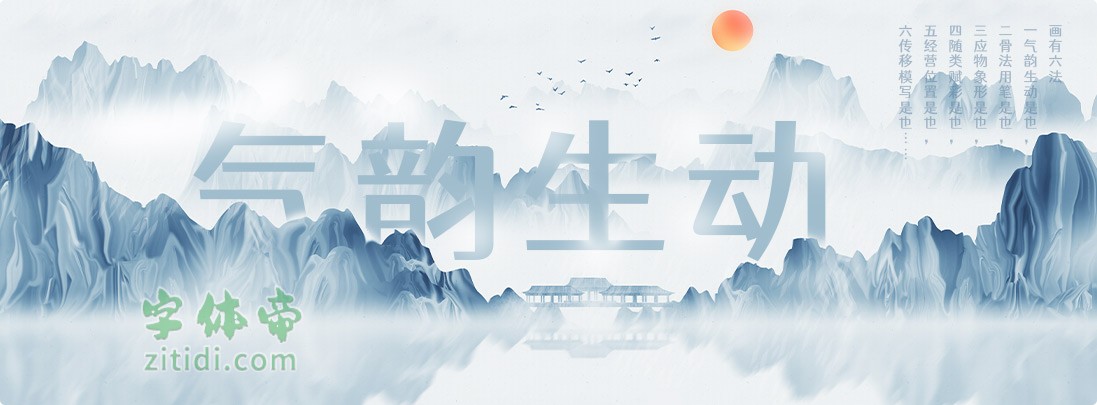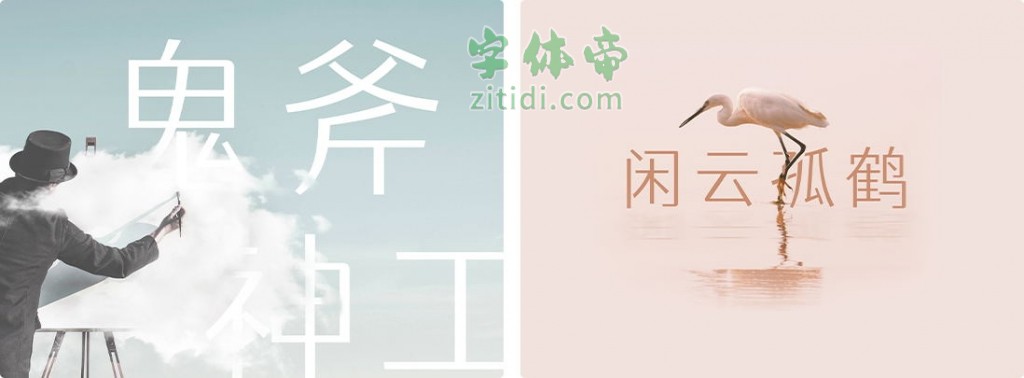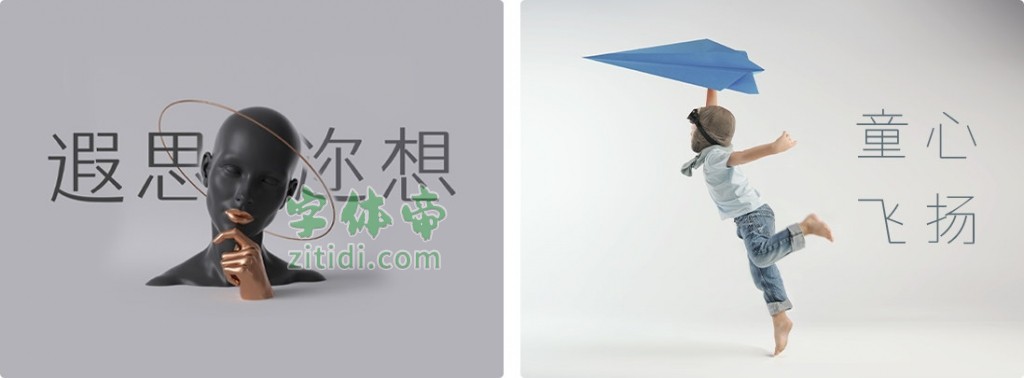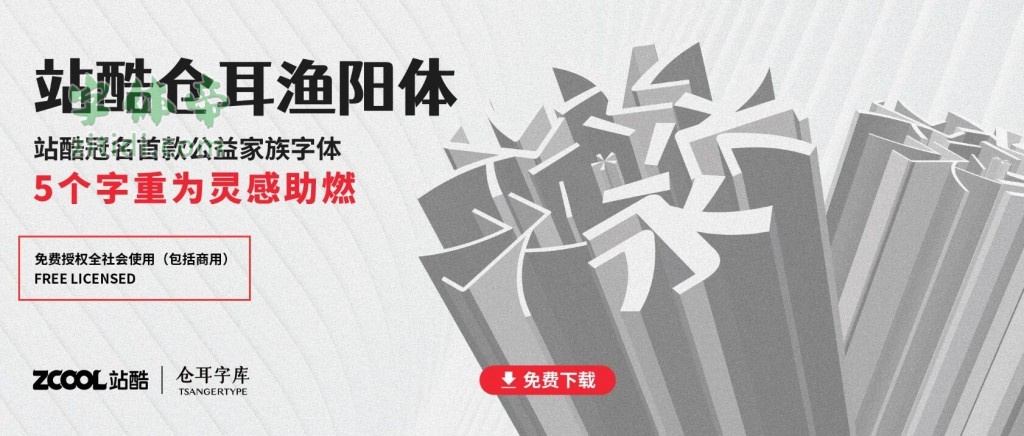
站酷仓耳渔阳体是仓耳字库在2020新冠疫情期间为造福社会奉上的一份礼物,也是站酷冠名的首款拥有家族字体的公益字库。字形结合宋、黑二体的结构特点,将部分笔画转折处做圆角处理,方圆结合,厚重又不失灵动。家族字体包含5个字重,均可免费商用,2020年9月发布第一版。
“仓耳渔阳体 W01”是一款书写很新颖的字体,字体大方,适合各种设计作品使用!欢迎下载!